Có đến hàng trăm ngàn loại font chữ khác nhau, và từng ngày chúng ta lại thấy các diễn đàn update thêm nhiều loại font chữ mới. Chính bằng việc có quá nhiều font chữ cân phải lựa chọn kiến các designer đau đầu để có thể chọn font chữ cho phù hợp. Tuy nhiên, có những font chữ đã được tạo ra từ rất lâu nhưng chưa bao giờ trở nên lỗi mốt. Hơn nữa, xu hướng thiết kế tối giản, nhất là trong thiết kế logo, khiến cho các designer quay về với các font chữ đơn giản, cũ mà tinh tế, thanh thoát.
Hãy cùng ITPlus Academy tìm hiểu 5 loại font không bao giờ lỗi mốt và trường tồn với xu hướng thiết kế của thế giới trong hàng chục năm qua.
Futura
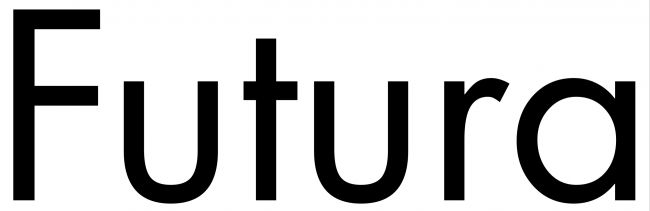
Được thiết kế bởi Paul Renner vào năm 1927, Furura được coi là cha đẻ của dòng font San serif – font chữ được lựa chọn nhiều nhất trong xu thế thiết kế tối giản ngày nay. Rất nhiều công ty và thương hiệu lớn xây dựng logo bằng font chữ này như Google, Mastercard hay Spotify và cũng là cảm hứng cho hàng chục thương hiệu khác như Alfa Romeo, Domino’s Pizza.
Những nét chữ mềm mại, đều đặn và thanh thoát, Futura chính là biểu tượng của sự mềm mại nhưng sang trọng và cứng cáp.
Caslon
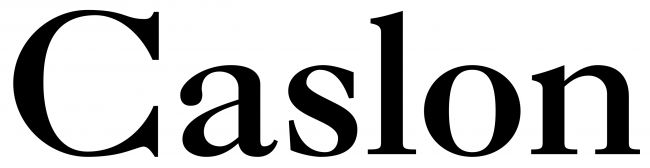
Lấy cảm hứng từ nét chữ của William Caslon (1692 – 1766), nét thanh lịch, sang trọng và quý phái của những người dân Anh Quốc thế kỷ 18 đã được thể hiện qua đường nét chắc chắn và tao nhã. Font chữ này được sử dụng rất nhiều trong các cuốn sách, tạp chí, bách khoa toàn thư,…
Garamond
Một lựa chọn khác trong việc truyền tải nội dung mang tính chất sang trọng, quý phái.
Clarendon
Nếu Caslon hay Garamond mang đến những hình ảnh của những quý ông tao nhã của Châu Âu xưa, thì Clarendon lại phảng phất hình ảnh những biển hiệu của các cửa hàng trên đường phố Paris – Pháp hay Venice, Italia. Nét thanh lịch cổ điển nhưng thoải mái với các đường nét bo tròn của font chữ Seriff này sẽ là cảm hứng cho các designer thiết kế các ấn phẩm liên quan tới các sản phẩm hay cảm hứng từ châu Âu một cách rất hiệu quả.
Akzidenz Grotesk
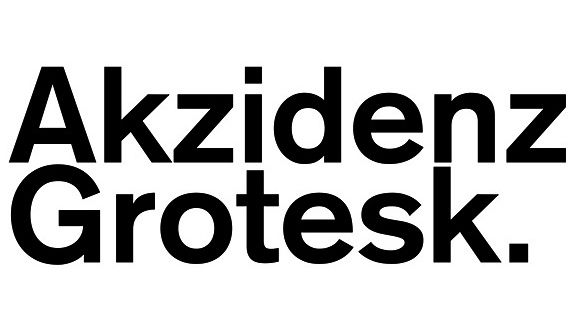
Font chữ Helvetica là một font chữ khá quen thuộc với chúng ta và được sử dụng rộng khắp trên thế giới. Nhưng Helvetica chỉ là “người đàn em” so với Akzidenz Grotesk, được giới thiệu lần đầu tại Berlin 1898. Akzidenz Grotesk là font chữ thích hợp cho các hình ảnh mang sự năng động nhưng không kém phần trưởng thành, chỉn chu bằng các nét chữ rất đều.
Trên đây là 5 font chữ cổ điển cho các designer đang muốn tìm cho mình một làn gió mới, một ý tưởng mới về những hình ảnh cổ điển nhưng mang đậm sự quý phái, những dấu ấn không bao giờ lỗi mốt trong xu hướng thưởng thức các tác phẩm thiết kế đồ họa hiện nay.